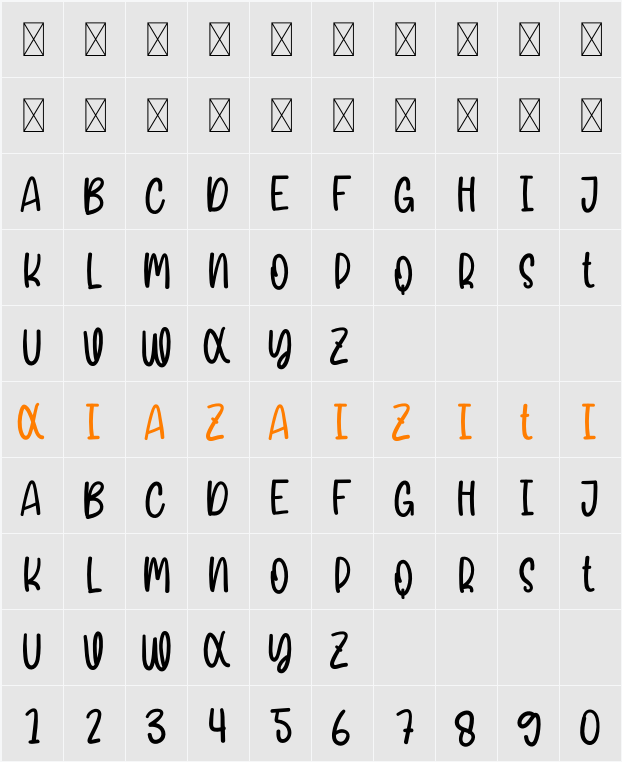
Winter Vacation
Winter Vacation,这款字体结构工整、笔画清晰,兼顾美观与易读性,适用于标题、正文、海报、包装、LOGO 等多种场景。字形优雅稳定,风格百搭耐看,适配日常排版与创意设计,让文字呈现更舒适、更具质感。Winter Vacation一笔一画,皆是细节,以均衡的比例、流畅的线条打造舒适视觉体验,字形端正大气,风格简约现代。无论是商业设计、品牌宣传还是日常排版,都能轻松驾驭,让文字更有格调与力量。Winter Vacation字体下载。